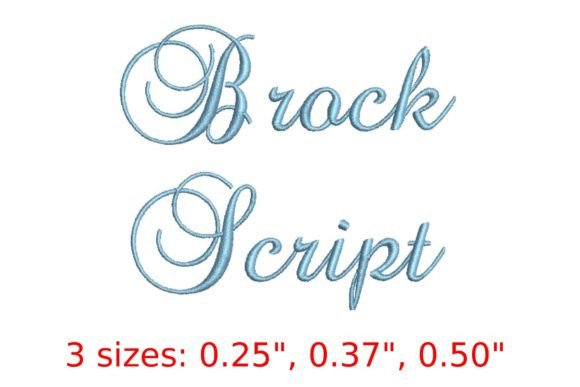
Brock Script Embroidery Font
Được chế tác với độ chính xác cao, Brock Script Embroidery Font cung cấp các vector sạch, kiểu chữ mượt mà và giấy phép thương mại để bạn yên tâm.